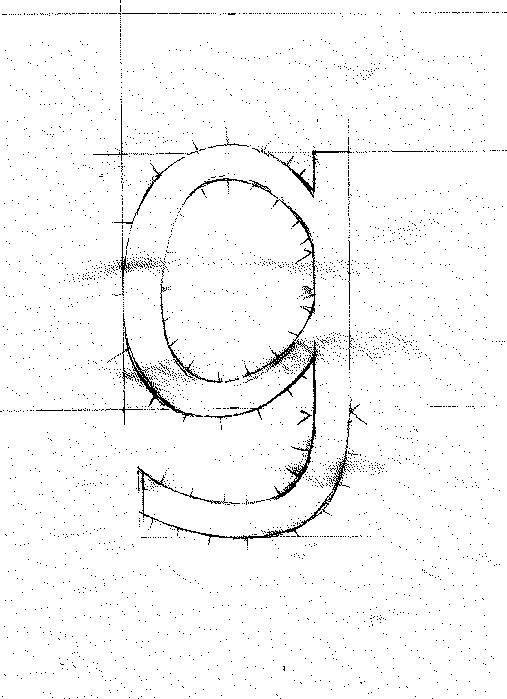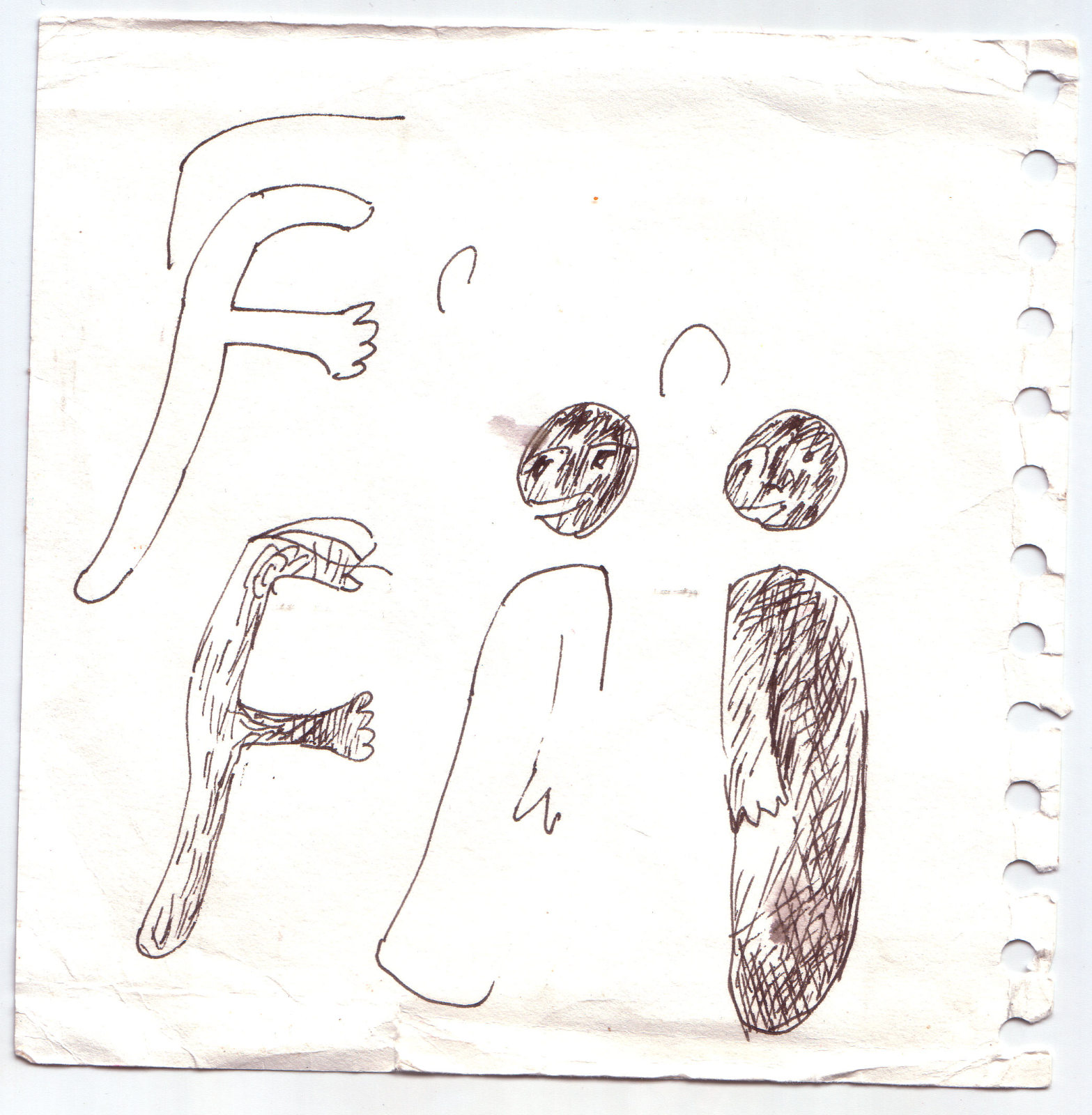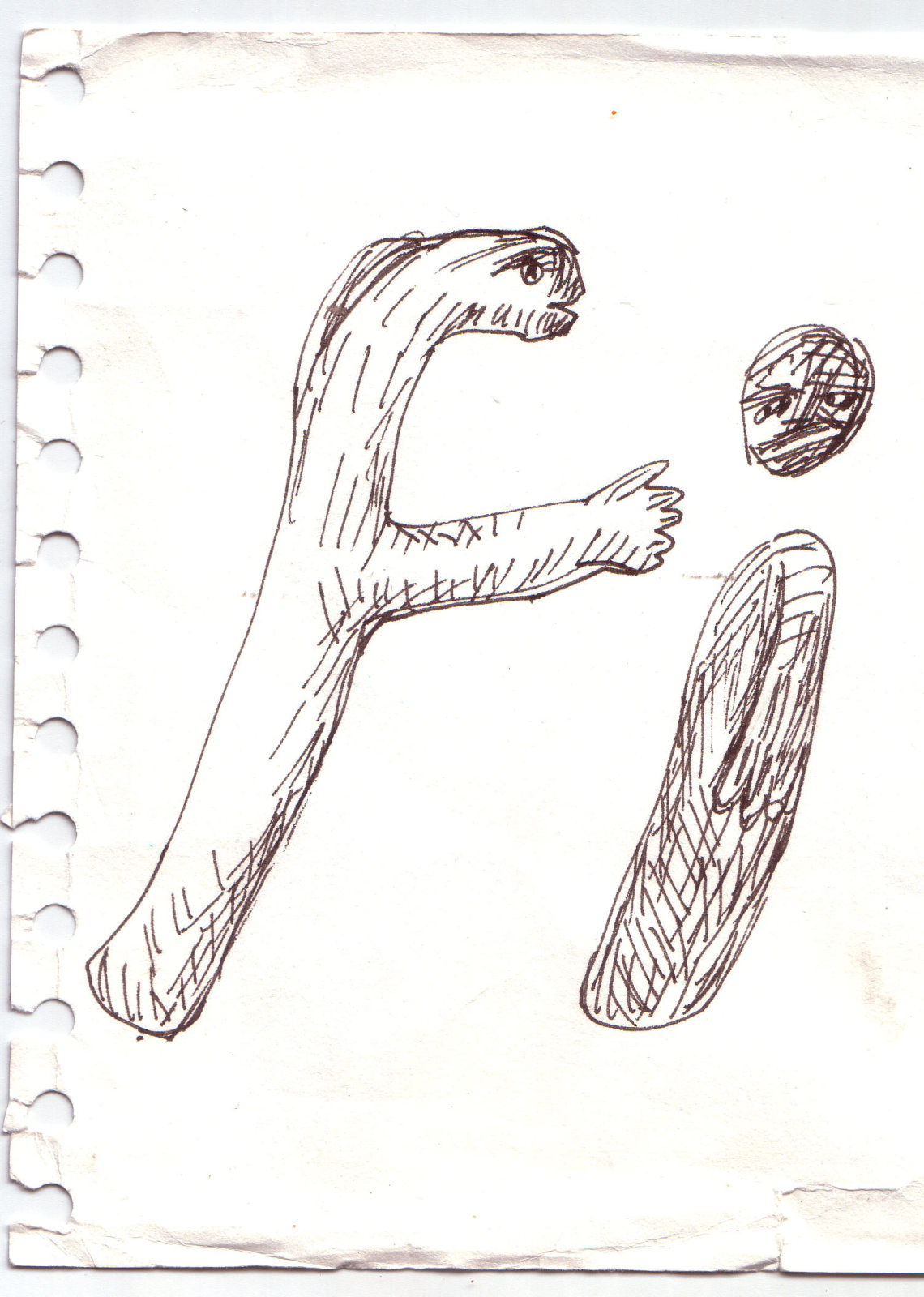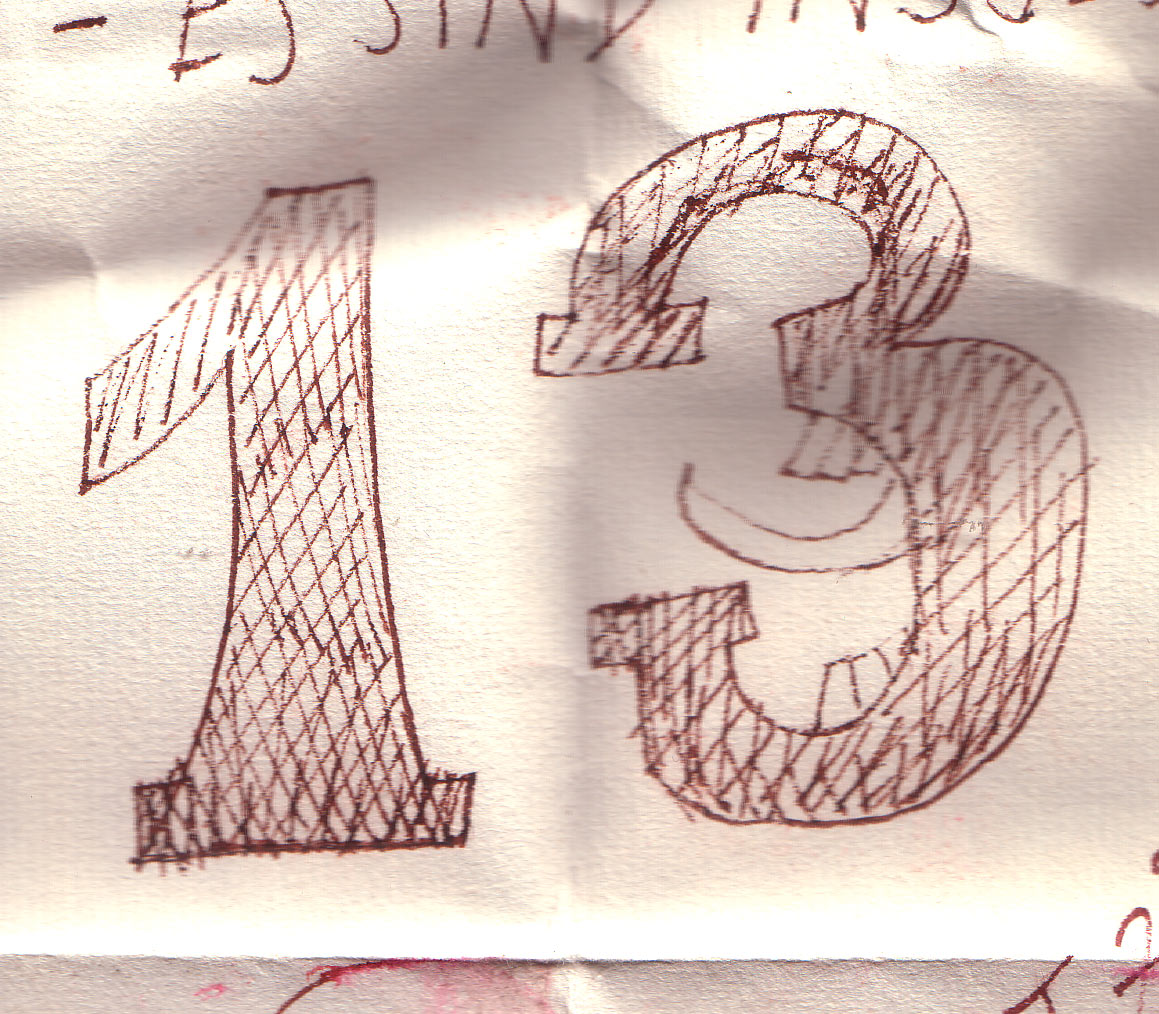
Was für Erkennungsbuchstaben habt ihr?
Darin sind eigentlich zwei Fragen enthalten:
1. Schaut ihr wenn ihr Schriften vergleicht, auf einen bestimmten Buchstaben? Oder eine bestimmte Gruppe? Bei mir ist es zunächst das kleine »a«, daneben weitere Buchstaben.
2. Was habt ihr so im Gedächtnis für markante Buchstaben verschiedener Schriften? Es gibt ja immer wieder Buchstaben, die in einer Schrift hervorstechen, während andere dies nicht so tun. Ich bin mal bei mir mein bescheidenes Schriftenmenü durchgegangen und habe für mich markante Buchstaben einiger Schriften zusammengetragen. (Edit: a/e/R bei der Arial sind auch typisch, insofern als man an ihnen klarer den Unterschied zur Helvetica bemerkt als bei manch anderen Buchstaben)
Mein Verhältnis zur Typografie ist wohl insofern immer schon etwas ungewöhnlich gewesen, als dass ich neben der eigentlichen Botschaft auch den Schriften erhöhnte Aufmerksamkeit geschenkt habe, bis zum Anstarren einzelner Buchstaben, was mich schlussendlich auch zu diesem Thread brachte.
Beruhigend zu wissen, dass das anderen genauso geht! :gimmifive:
Ich schau auch immer zuerst auf das kleine a, daneben auch natürlich auf das g und das auch von dir genannte Q. Kommt natürlich immer drauf an. Wenn ich durch das Anstarren z.B. eine bestimmte Schrift identifizieren will und ich schon so einen Verdacht habe, rufe ich mir die Besonderheiten dieser Schrift ins Gedächtnis und suche speziell danach (z.B. den kleinen Sporn oben beim s der Albertina, der tangentiale Schweif der Adobe Caslon ...). Das sind natürlich oft Merkmale, die mehrere Schriften haben. Je mehr Übereinstimmungen man daher findet, desto schneller erlangt man Gewissheit.
kommt immer drauf an. manchmal ist es auch nur die anmutung, das gefühl, die ausstrahlung einer schrift, die sie verrät. der blick auf für diese schrift typische glyphen ist dann oft nur mehr die bestätigung.
Sagt mal, geht's euch eigentlich auch so wie mir, dass für euch manche Buchstaben männlich, manche weiblich sind? Ich will ja nicht schon wieder eine Gender-Debatte vom Zaun brechen, aber für mich persönlich ist z.b. das a männlich, das f weiblich, usw., ohne dass ich inmer genau sagen kann, warum.
Hmm, kann ich nicht von mir sagen... Ich finde aber auch, dass Buchstaben, und dann auch abhängig von Schriften, auf mich wie gewisse Charaktere wirken. Auf diffuse Weise. Eben diese Anmutung, die nicht nur im Schriftbild, sondern auch bei einzelnen Buchstaben existiert.
Geht mir auch so, und ich hab mich mal gefragt, wie sich diese unterschiedlichen Charaktere so fühlen, also so im Wortzusammenhang, davon sind anscheinend nur noch diese Skizzen übriggeblieben (ist vielleicht auch besser so). Also ein aufdringliches f neben einem unnahbaren i. Die 13 ist noch von einer Schatzsuche übriggeblieben (out comes the freak ;-) ). Ansonsten hab ich eigentlich keine echten Präferenzen, aber das kleine g hatte ich mal richtig gern (und alles andere mit Bäuchen, so p, q, a, b usw.) Naja, und zu dem gender-Ding: soweit wie Spiekermann würde ich nicht gehen …
Und jetzt nicht mehr? *stutz*
Hhmm … naja, wie soll man es möglichst diplomatisch sagen, is ja immer schwierig mit der Liebe. Erst war es eine zarte Bleistift-Outline und die Ahnung eines Buchstabens und sogar der Parameter eines Alphabets, dann ist es eine Schrift geworden, oder Teil einer solchen. Es hat sich verändert, sozusagen, die Beziehung wurde dann doch arg versachlicht, Illusionen mussten begraben werden usw.
Ich habe beispielsweise an mir selbst gemerkt, wie sich bei mir typographische Standards verändert haben. Früher als Jugendlicher hatten mich Weißräume noch gestört. Dann hatte ich die Buchstaben enger beeinander (also verschmälert, oder was sagt man dazu), und den Satzspiegel so groß wie möglich gehalten. Mittlerweile verkleinere ich beispielsweise den Standard-Satzspiegel von OpenOffice von 2 cm links und rechts zu 2,5-2,7 cm, weil das erstens eleganter aussieht und zweitens die Zeilen näher an ihre Optimallänge von etwa 60 Zeichen geführt werden. Zudem setze ich die Zeilen weiter auseinander als bei den allermeisten Schriften festgelegt (was auch sinnvoll ist, da die Zeilen bei DIN A4 auch zumeist länger sind als sonst).
Noch eine Anekdote: Ich war mal in der hiesigen Zentralbibliothek, und schaute Prospekte durch, auf der Suche nach neuen Schriftbeispielen. Eine Frau neben mir schaute mich etwas misstrauisch an, worauf ich sagte, was ich tat. Daraufhin schaute sie mich noch befremdeter an, weil sie sich nicht vorstellen konnte, wie sich jemand mit so einer Nebensächlichkeit aufhalten könnte! :)
Schlussendlich läuft es oft auf eine der Grundsatzfragen im Design hinaus - das Spannungsverhältnis zwischen Schönheit und Zweckmäßigkeit, zwischen Form und Funktion (wobei Ästhetik eine Funktion in sich sein kann, wie ich finde). Optimalerweise ergänzen sich beide Aspekte - sodass eine Schrift gut lesbar ist und zugleich eine schöne Anmutung hat. In der Antiqua beispielsweise ist das recht gut gelungen - ihre kalligraphischen Ursprünge verleihen ihr sowohl eine Eleganz als auch eine gute Lesbarkeit durch die Mannigfaltigkeit der Formen.
Ja, mit der Ästhetik ist das immer so eine Sache ... Ich weiß manchmal nicht, ob ich etwas schön finde, weil es zeitlos schön ist, oder weil ich nur durch meine Umgebung drauf konditioniert bin. Ich finde die Antiqua auch schön - aber woran liegt das eigentlich? Kalligrafische Ursprünge, Eleganz und Mannigfaltigkeit der Formen kann die Fraktur auch aufweisen.
Das mit den veränderten Standards, was du erwähnt hast, kenne ich auch. Man hat dann plötzlich ganz andere Ansichten als Nicht-Eingeweihte.
Eine weitere Anekdote: Erst vorgestern habe ich einer Freundin Schriftentwürfe von mir gezeigt, die daraufhin ganz perplex wissen wollte, wie man denn Schriften entwirft. Da fällt einem erstmal nix dazu ein ... Ich finde, das ist auch immer ein bisschen der Reiz an Typografie und Schriftgestaltung, dass es eine Kunst ist, die von einem Großteil der Menschheit einfach nicht wahrgenommen, weil vorausgesetzt wird. Das verhindert einen allzu großen Hype um Einzelpersonen und schafft ein professionelles Umfeld.
Man müsste einmal Kleinkinder fragen, was sie von Buchstaben halten - sie können ja noch nicht lesen und sind in ihrem Empfinden noch nicht so stark beeinflusst worden. Wir sind vermutlich daran gewöhnt, dass alle Buchstaben, die wir kennen, auf eine bestimmte Weise auszusehen haben. Das O zum Beispiel hat aber eine reinere Form als das G. Ich könnte mir vorstellen, dass das G hässlicher aussähe, wenn man es nicht kennen würde. Vielleicht sieht das kyrillische Alphabet für uns Westler hässlicher aus als für Russen. Ich finde jedenfalls das griechische Alphabet mit seinen vielen geometrischen Grundformen außerordentlich schön. Das fand ich damals, als ich es noch nicht lesen konnte, und jetzt auch noch, wo ich es lesen kann.
1124jk9.jpg
Es ist eigentlich die Frage, welche Rolle die Ästhetik in jedem Kontext spielt. Dass Schriftästhetik nur für sich selbst interessant ist, ist - möglicherweise - eine Besonderheit von uns Leuten hier, oder für uns jedenfalls wesentlich wichtiger. Dann kann Ästhetik natürlich über die Anmutung einer Schrift, über die Assoziationen, ihre Suggestionen in eine bestimmte Richtung, eine Funktion haben, nämlich wenn sie mit den Assoziationen des Produktes übereinstimmt. Dann übernimmt die Schrift kommunikative Aufgaben über ihre eigentlichen phonetischen Aufgaben hinaus. Zu guter Letzt, oder vielmehr zuförderst, ist Schrift ein Mittel, um gesprochene Sprache zu konservieren und lesbar zu machen. Ästhetik kann dann auch hinderlich sein, wenn sie vom Inhalt ablenkt, wenn Schrift optimal lesbar sein muss und wegen ihrer eigenen Ästhetik schlechter lesbar wird. Je nach Einsatz der Schrift sind die verschiedenen Aspekte dann unterschiedlich gewichtet. Ich kann mir auch vorstellen, dass es Typographen gibt, die die ästhetische Seite gänzlich für störend halten. Ein Hinweis dafür könnte auch sein, dass manche Typographen in der Schriftentwerfen eine Kunst oder einen Kunstaspekt sehen, andere wiederum eine sehr ingenieurhafte, rein handwerkliche Vorstellung von Typografie haben. Besonders kontrovers dürfte die Frage sein, ob Schrift eine Form persönlichen künstlerischen Ausdrucks sein darf, wenn sie professionell betrieben wird. Schließlich ist die Fragestellung eigentlich andersherum gestaltet - was sind die Anforderungen an eine Schrift? Der persönliche Ausdruckswille könnte aber durchaus seinen Zweck haben, wenn er mit Bedürfnissen der potentiellen Nutzer zusammentrifft. Beispielsweise, wenn ein Schriftgestalter eine bestimmte, für ein bestimmtes Umfeld passende Anmutung erreicht, und es dabei auch schafft, die formalen Kriterien einer gut gestalteten Schrift zu erfüllen.
Ich weiß zwar nicht, ob das mit der Kleinkinderbefragung funktionieren würde, aber einen Versuch wäre es mal wert ...
Ich mag das griechische Alphabet auch sehr gerne! Die geometrische Anmutung kommt wohl daher, dass es näher am linearen Duktus der alten Schriftsysteme liegt. Das Alphabet, das du gezeigt hast (Times?), versucht ja schon, die Buchstaben "einzuantiquaisieren".
Ich weiß zwar nicht, ob das mit der Kleinkinderbefragung funktionieren würde, aber einen Versuch wäre es mal wert ...
Ich mag das griechische Alphabet auch sehr gerne! Die geometrische Anmutung kommt wohl daher, dass es näher am linearen Duktus der alten Schriftsysteme liegt. Das Alphabet, das du gezeigt hast (Times?), versucht ja schon, die Buchstaben "einzuantiquaisieren".
Richtig - in der Sans-Version wären die Formen reiner.
um noch mal aufs Thema zurückzukommen: es sei noch an diese site erinnert, die den schönsten Einzelbuchstaben von Georg Salden gewidmet ist